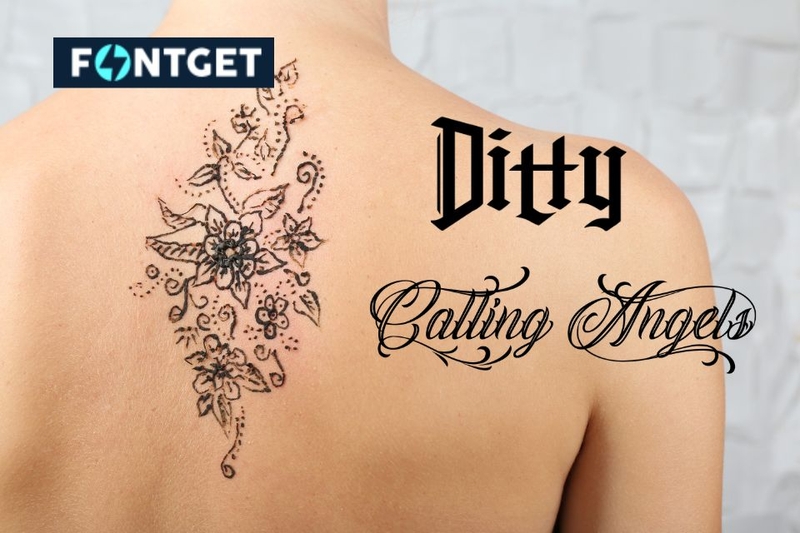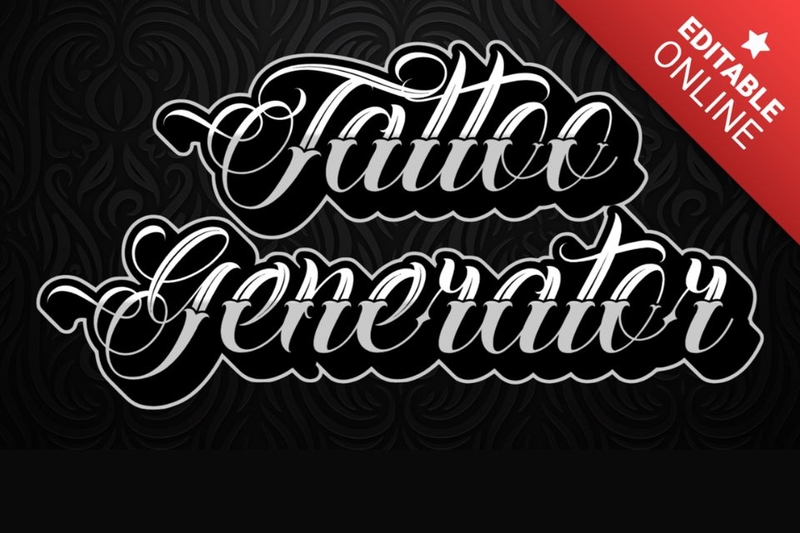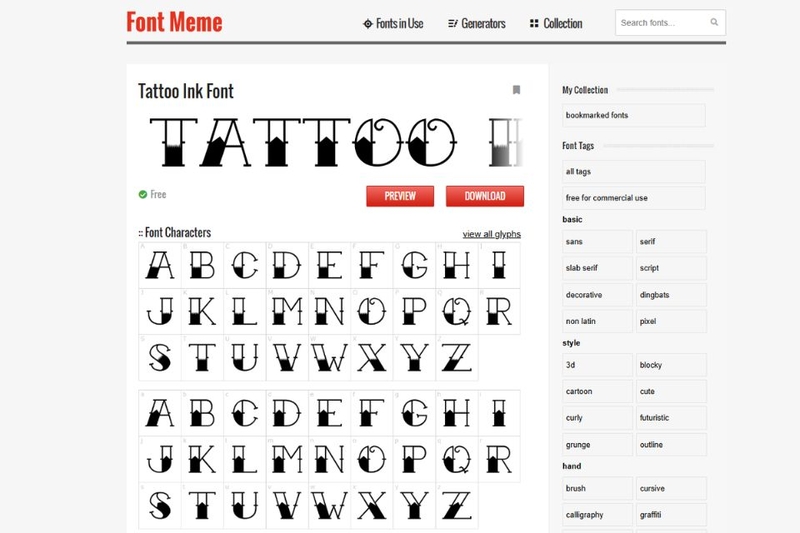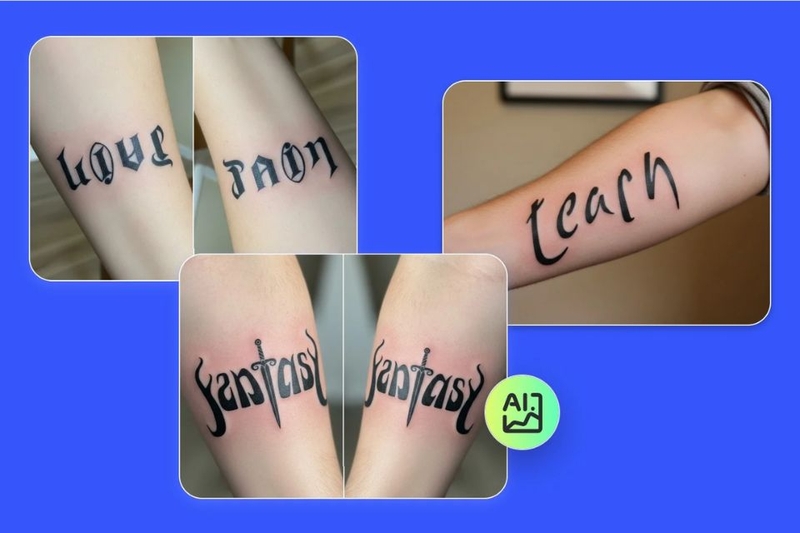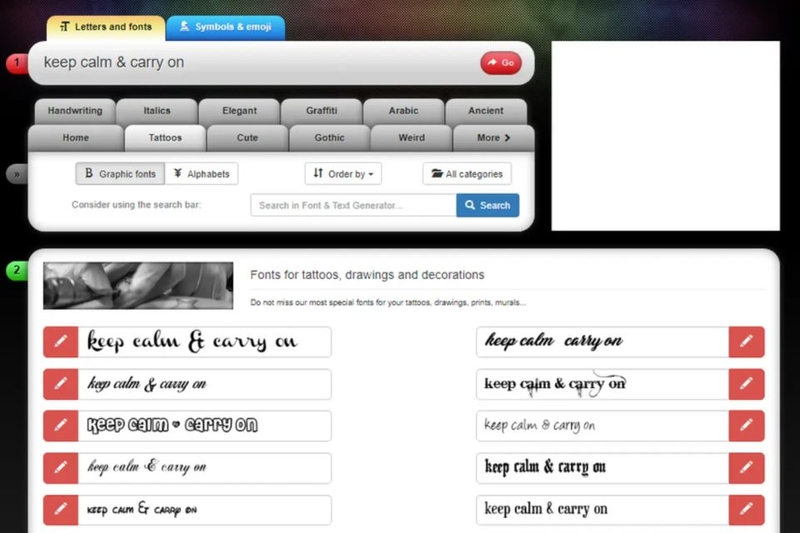
Top 8 công cụ tạo font chữ tattoo online đẹp, miễn phí trong vài phút
Trong vài năm gần đây, xu hướng tạo font chữ tattoo online ngày càng được ưa chuộng. Thay vì phải ngồi hàng giờ cùng thợ xăm để phác thảo từng nét chữ, giờ đây bạn có thể tự thiết kế trước kiểu chữ mình yêu thích chỉ trong vài phút. Các công cụ trực tuyến tích hợp AI không chỉ giúp tiết kiệm thời gian mà còn mở ra vô vàn phong cách sáng tạo. FPT Shop sẽ giúp bạn khám phá 8 nền tảng hỗ trợ tạo font chữ xăm trực tuyến nổi bật nhất hiện nay cùng những lưu ý quan trọng để chọn được công cụ phù hợp.
Vì sao nhiều người thích tạo font chữ tattoo online miễn phí?
Xu hướng tạo font chữ tattoo online miễn phí ngày càng phổ biến nhờ sự tiện lợi và khả năng tùy biến cao. Chỉ với vài thao tác đơn giản, bạn đã có thể tự thiết kế kiểu chữ xăm đúng với cá tính của mình.
- Tự do sáng tạo: Bạn có thể thử nghiệm hàng chục phong cách khác nhau trước khi quyết định.
- Tiết kiệm chi phí: Không cần thuê designer riêng để phác thảo chữ.
- Nhận phản hồi ngay lập tức: Chỉ vài giây là bạn đã có bản xem trước hoàn chỉnh.
- Phù hợp mọi trình độ: Dù bạn không biết thiết kế, các công cụ AI vẫn hỗ trợ tối đa.
- Cá nhân hóa tối đa: Bạn có thể tạo kiểu chữ mang dấu ấn riêng thay vì dùng mẫu có sẵn.
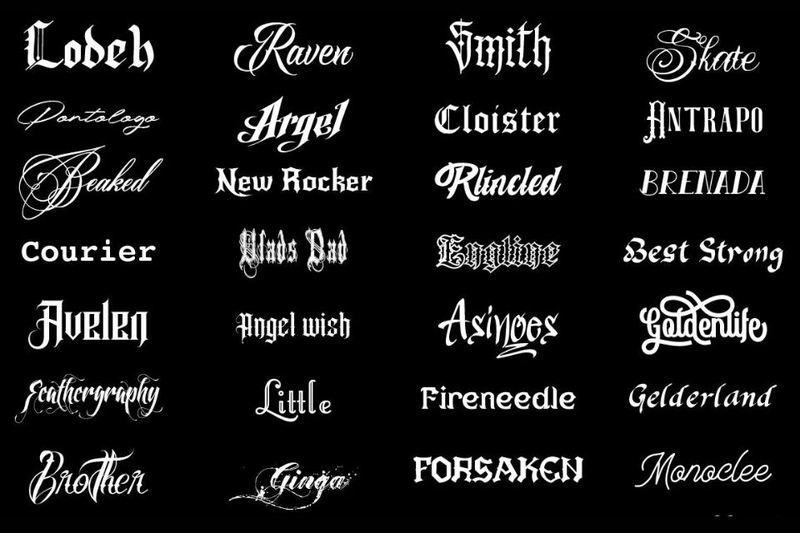
Những tiêu chí quan trọng khi chọn công cụ tạo font chữ tattoo online
Để tạo font chữ tattoo trực tuyến vừa đẹp vừa phù hợp với cá tính, việc lựa chọn đúng công cụ là yếu tố rất quan trọng. Dưới đây là những tiêu chí bạn nên cân nhắc trước khi quyết định sử dụng bất kỳ nền tảng nào.
Đa dạng phong cách chữ
Một công cụ tốt cần cung cấp nhiều kiểu chữ như gothic cá tính, thư pháp mềm mại, chữ máy đánh chữ cổ điển hay chữ khối hiện đại. Sự đa dạng này giúp bạn dễ dàng chọn phong cách phù hợp với ý nghĩa và cá tính riêng của mình.
Khả năng tùy chỉnh
Hãy ưu tiên nền tảng cho phép thay đổi kích thước, giãn cách ký tự, căn chỉnh bố cục cũng như thêm hiệu ứng bóng hoặc đổ màu. Khả năng tùy chỉnh linh hoạt sẽ giúp thiết kế trở nên độc đáo và đúng với mong muốn ban đầu.
Xem trước trực quan
Tính năng preview giúp bạn hình dung chữ xăm khi đặt trên nền da hoặc mockup cơ thể. Điều này giúp hạn chế sai sót và đảm bảo thiết kế trông hài hòa trước khi xăm thật.
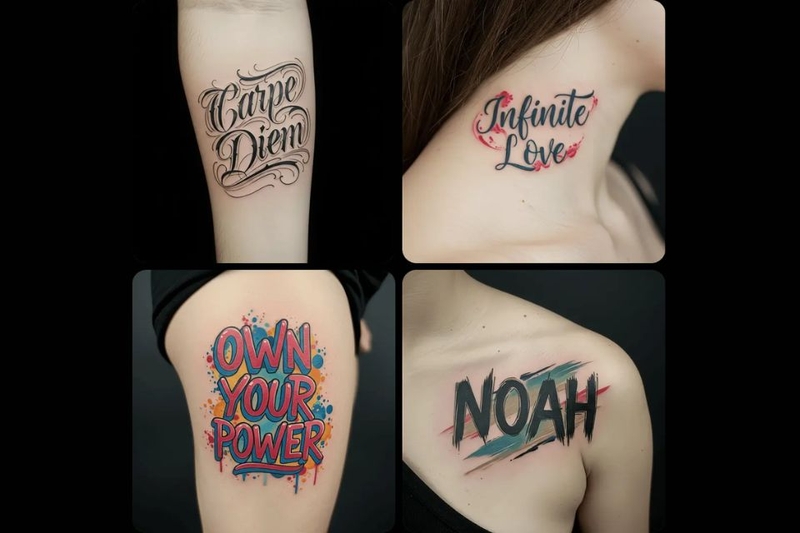
Chất lượng file xuất
Chất lượng file xuất là yếu tố không nên bỏ qua khi tạo font chữ tattoo online. File có độ phân giải cao sẽ đảm bảo các đường nét hiển thị sắc nét, không bị vỡ hoặc mờ khi phóng to. Điều này đặc biệt quan trọng vì thợ xăm sẽ dựa trên bản thiết kế để thực hiện từng chi tiết nhỏ trên da. Nếu file quá thấp chất lượng, các nét mảnh hoặc hiệu ứng tinh tế có thể bị sai lệch, ảnh hưởng đến kết quả cuối cùng.
Dễ sử dụng
Một công cụ có giao diện trực quan, bố cục rõ ràng và thao tác đơn giản sẽ giúp bạn tiết kiệm đáng kể thời gian thiết kế. Ngay cả khi chưa có kinh nghiệm về đồ họa, bạn vẫn có thể dễ dàng nhập nội dung, chọn kiểu chữ và điều chỉnh theo ý muốn.
Top 8 công cụ tạo font chữ tattoo online nổi bật nhất
Nếu bạn đang tìm cách tạo font chữ tattoo online nhanh chóng, dễ sử dụng và đa dạng phong cách, danh sách dưới đây sẽ giúp bạn chọn đúng công cụ phù hợp. Từ nền tảng AI hiện đại đến thư viện font miễn phí, mỗi công cụ đều có thế mạnh riêng để hỗ trợ thiết kế chữ hình xăm cá nhân hóa.
Dreamina
Dreamina là nền tảng thiết kế sử dụng trí tuệ nhân tạo, nổi bật với tính năng “AI Text Effect” cho phép biến ý tưởng chữ viết thành thiết kế hình xăm độc đáo chỉ sau vài giây. Nếu bạn đang tìm một công cụ tạo font chữ tattoo online có khả năng tùy chỉnh cao, đây là lựa chọn đáng cân nhắc.
Sau khi đăng nhập, chọn mục Canvas và nhập nội dung bạn muốn xăm (tên, câu nói, ký hiệu,…). Sau đó bạn nhập mô tả chi tiết về phong cách mong muốn như: “chữ đỏ đậm phong cách gothic”, “thư pháp mềm mại màu đen”, “chữ mờ hiệu ứng khói”,… AI sẽ tự động đề xuất nhiều biến thể khác nhau. Bạn có thể chỉnh kích thước, giãn cách chữ, căn lề, thêm layer nền hoặc thay đổi bố cục. Sau khi hoàn thiện, xuất file độ phân giải cao để in hoặc gửi cho thợ xăm.
Điểm mạnh của Dreamina là khả năng tùy chỉnh nâng cao như thay đổi kích thước, khoảng cách và hiệu ứng chữ linh hoạt. Công cụ còn hỗ trợ nâng cấp ảnh HD, tạo nhiều lớp xem trước trên nền da, phù hợp cả người mới lẫn designer chuyên nghiệp.
FontSpace
FontSpace là một trong những thư viện font miễn phí lớn và lâu đời, được nhiều người lựa chọn khi cần tạo font chữ tattoo online. Nền tảng này cung cấp hàng nghìn kiểu chữ thuộc nhiều phong cách khác nhau, từ gothic mạnh mẽ, chữ viết tay mềm mại đến thư pháp cổ điển. Bạn có thể nhập nội dung trực tiếp để xem trước cách hiển thị trước khi tải xuống, giúp dễ dàng hình dung kiểu chữ sẽ trông như thế nào khi xăm lên da.
Ưu điểm lớn nhất của FontSpace nằm ở kho font đồ sộ và hoàn toàn miễn phí, kèm theo hệ thống đánh giá, nhận xét từ cộng đồng để tham khảo. Tuy nhiên, hạn chế của nền tảng này là không có công cụ chỉnh sửa nâng cao trực tiếp trên website, vì vậy bạn sẽ cần dùng thêm phần mềm khác nếu muốn tinh chỉnh sâu hơn về khoảng cách, hiệu ứng hoặc bố cục.